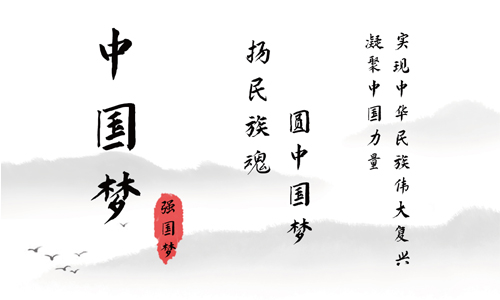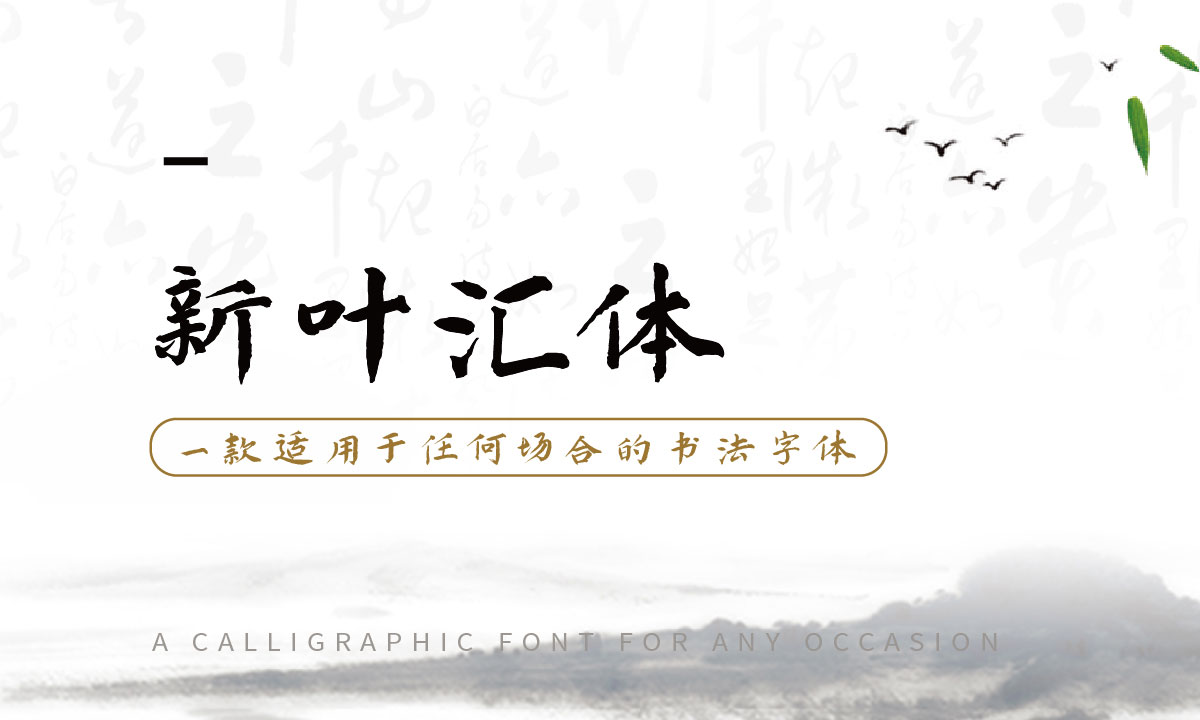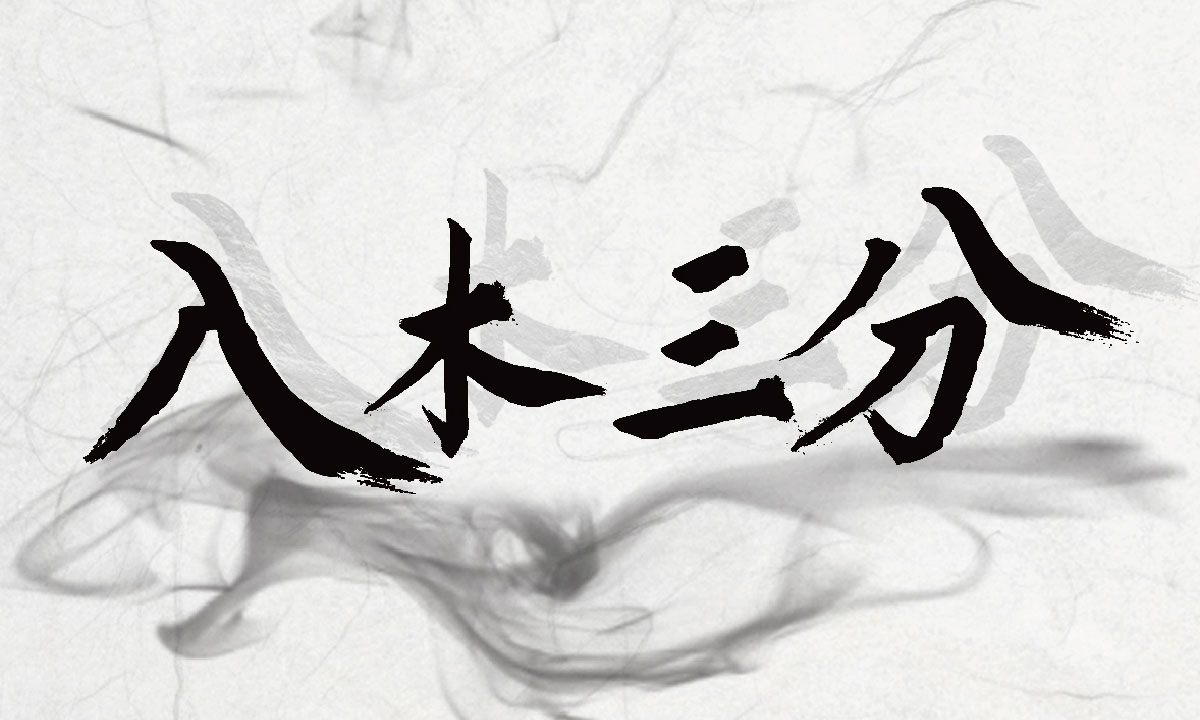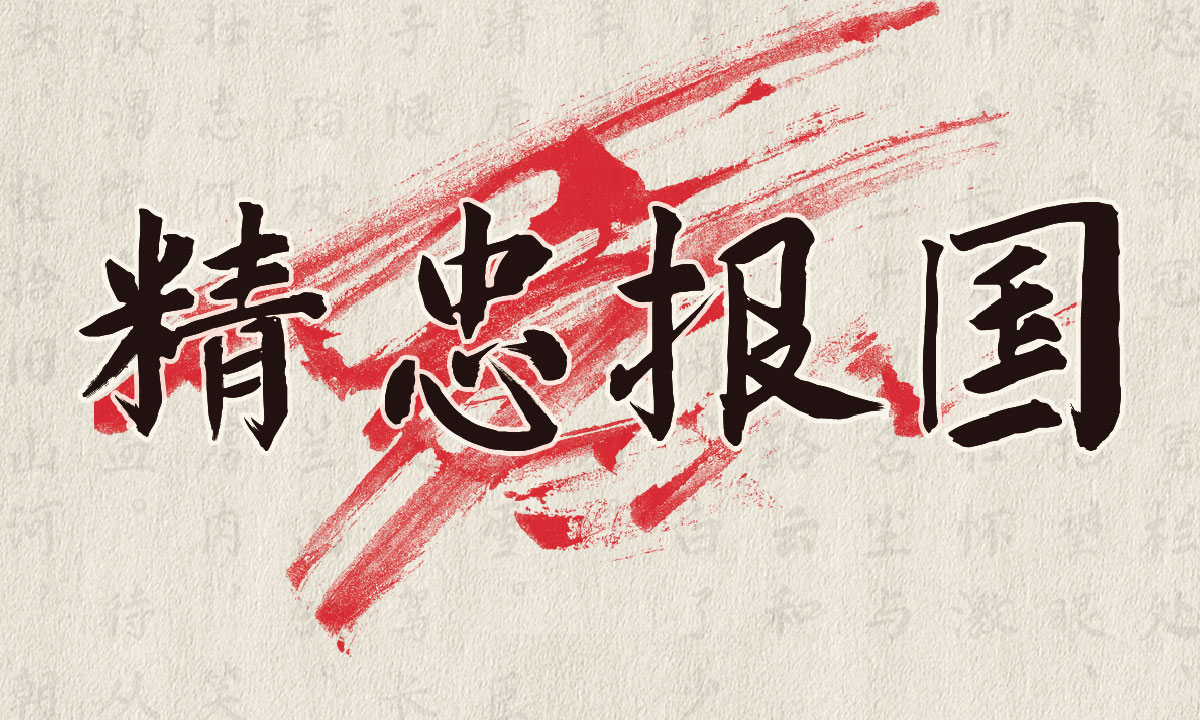
新葉匯體是一款適用于任何場(chǎng)景的書(shū)法字體,匯意為聚合之意,不積小流,無(wú)以匯江海。匯字力量巨大,大家一起相聚,匯之后則團(tuán)結(jié),團(tuán)結(jié)而后力量大。我們秉承著團(tuán)結(jié)之心,匯合之意設(shè)計(jì)這副字體,任何工作都需要相互合作。因此取團(tuán)隊(duì)協(xié)作之意命名為匯體。
我們也想要成為優(yōu)秀傳統(tǒng)文化傳承的一份子,我們想要成為傳承中國(guó)文化的一株小流,雖然這樣微不足道。但是小流匯多,則江??沙伞_@副字體看上去肆意灑脫,如流水一樣帶動(dòng)著流動(dòng)的氣息,卻形動(dòng)而神不散,也進(jìn)一步展示了匯的精髓。
字體名稱(chēng):新葉匯體